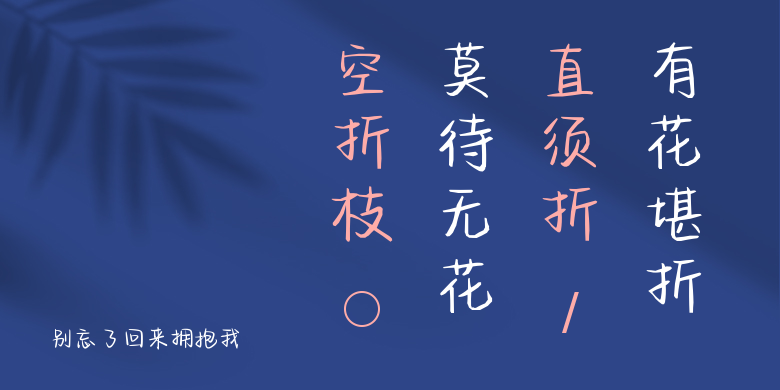
别忘了回来拥抱我
别忘了回来拥抱我,这款字体结构工整、笔画清晰,兼顾美观与易读性,适用于标题、正文、海报、包装、LOGO 等多种场景。字形优雅稳定,风格百搭耐看,适配日常排版与创意设计,让文字呈现更舒适、更具质感。别忘了回来拥抱我一笔一画,皆是细节,以均衡的比例、流畅的线条打造舒适视觉体验,字形端正大气,风格简约现代。无论是商业设计、品牌宣传还是日常排版,都能轻松驾驭,让文字更有格调与力量。别忘了回来拥抱我字体下载。